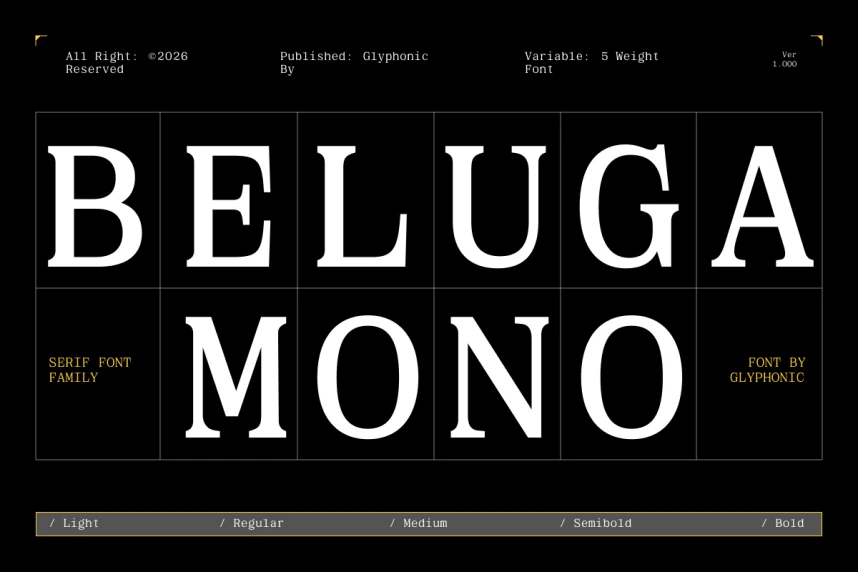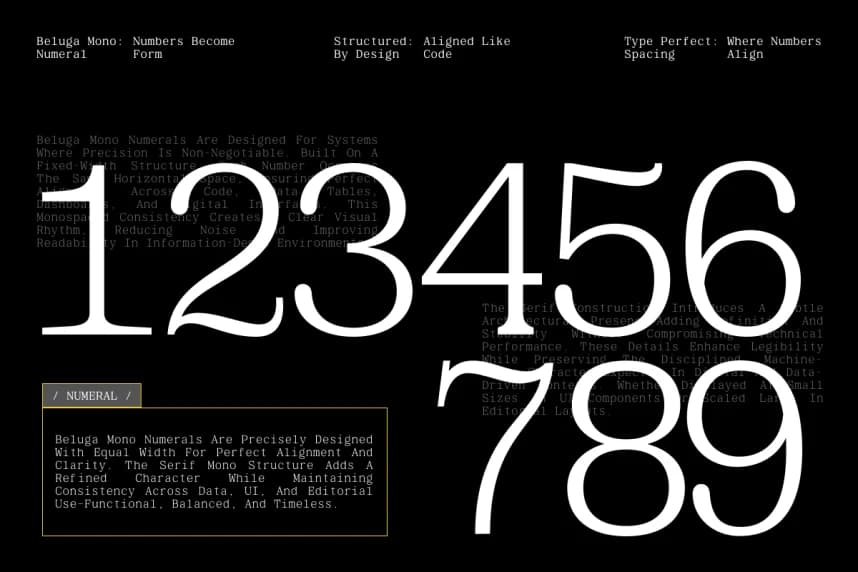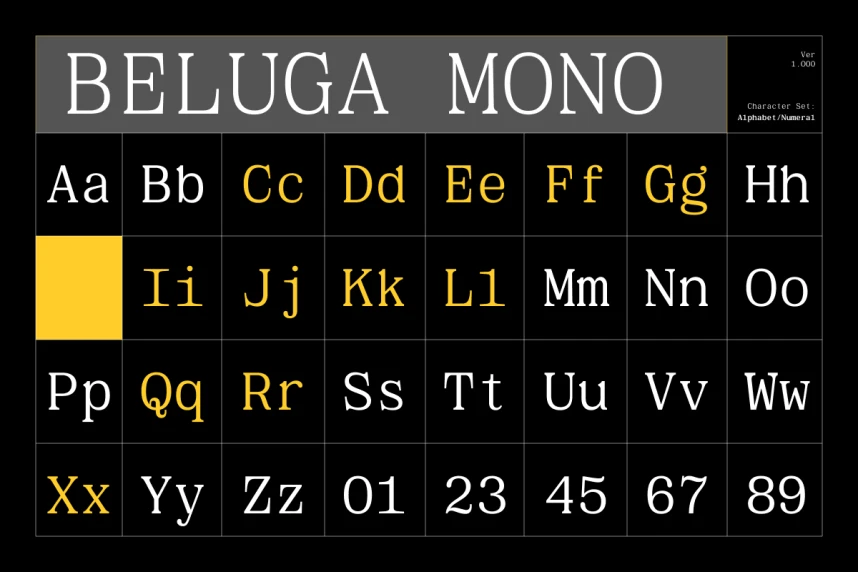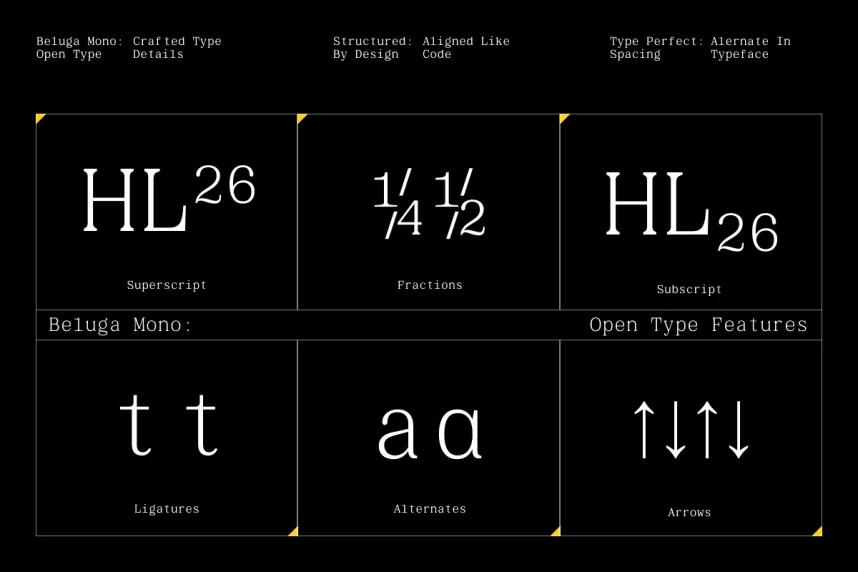
GC Beluga Mono Font
GC Beluga Mono Font – Elegant Modern Mono Serif, çağdaş bir yazı tipidir ve monospaced tasarımın hassasiyetini serif formlarının zarafetiyle birleştirir. Yapısal bir ızgara sistemi üzerinde kurulmuş ve ince serif detaylarıyla zenginleştirilmiş olan Beluga Mono, benzersiz bir tipografik ses sunar; bu
GC Beluga Mono Font – Elegant Modern Mono Serif, monospace tasarımının hassasiyetini serif biçimlerinin zarafetiyle birleştiren çağdaş bir yazı tipidir. Yapılandırılmış bir ızgara sistemi üzerinde inşa edilmiştir ve ince serif ayrıntılarıyla zenginleştirilmiştir; Beluga Mono, hem teknik hem de sofistike bir tipografik ses sunar.
GC Beluga Mono